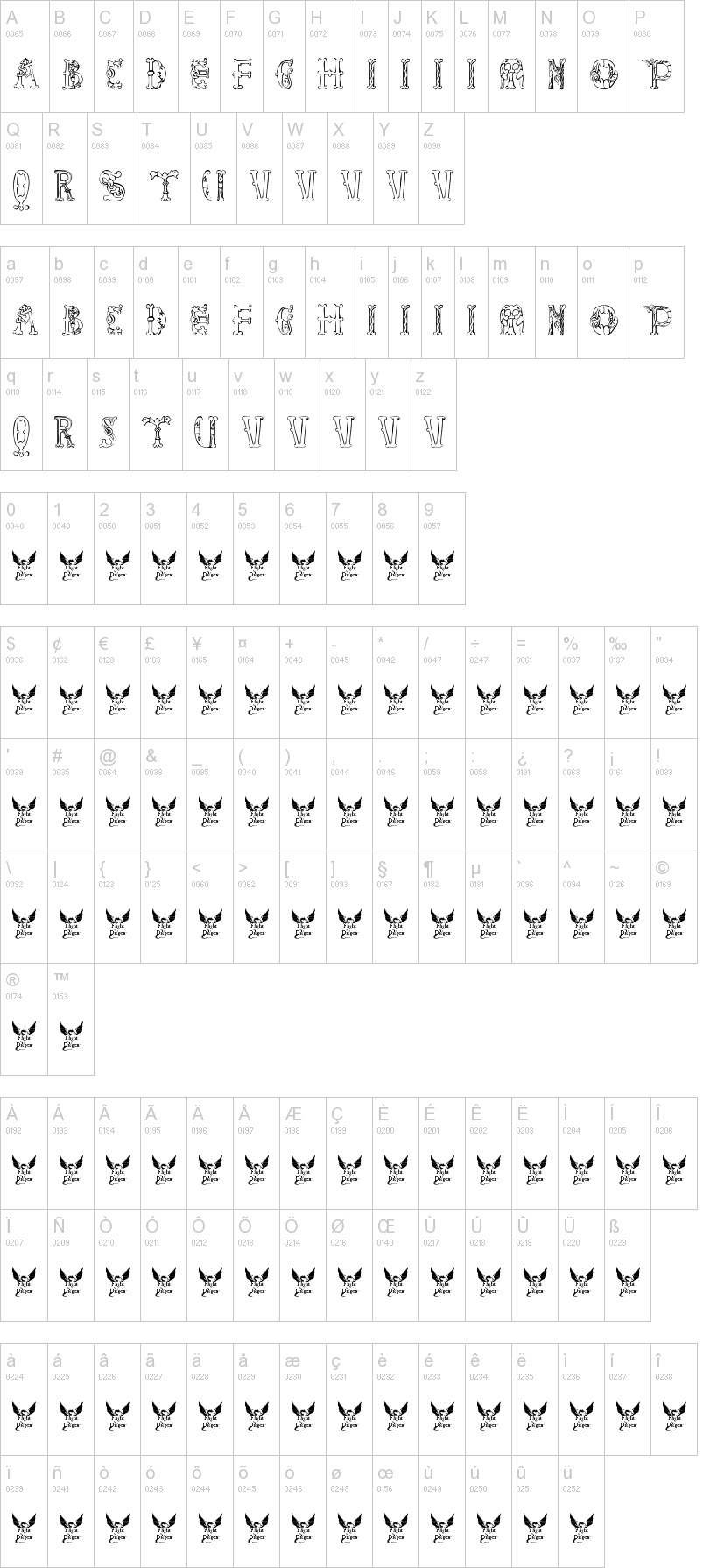
Library of Minerva, 9th c. 是一款古典风格的字体,由英国设计师Pablo Impallari创作。它受到了古罗马神庙Minerva的启发,具有细腻的细节和优雅的曲线,让人们联想到古老的文字。它的字母表现出了深厚的历史底蕴,是一款典雅的西方字体,适合用于海报、商标、标题等设计中。内容介绍
Library of Minerva, 9th c.是一款非常不错的手写艺术字体,具有很好的视觉感,适合于文化类的宣传设计、商业类品牌的广告和产品包装设计以及个性化文字排版等较多场景。